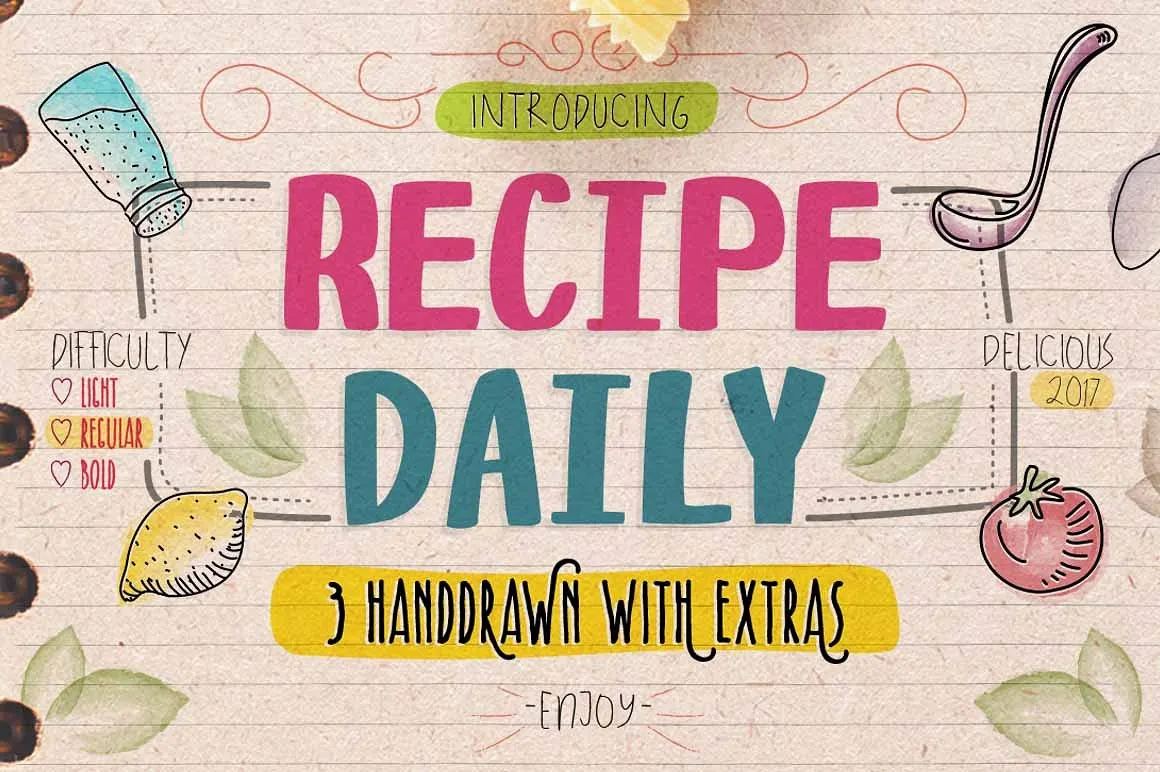
Recipe Daily Typeface – Download Grátis
Introduzimos Recipe Daily Typeface! Desenvolvida por StoricType, esta é uma fonte premium que você pode encontrar para compra na Críativa Mercado. Agora, recebemos a oportunidade de oferecer esta fonte gratuitamente para download. Recipe Daily Typeface surgiu inspirada em muitas letras encontradas nas anotações das refeições e foi projetada especificamente para as anotações de receitas e para o previsualização do Instagram. A fonte incorpora conceitos modernos em letras, logotipos, posters, camisetas e muito mais. Se você procura uma fonte que combine elegância com um toque contemporâneo, Recipe Daily é perfeitamente adequada. Sujeitada a um amplo espectro de aplicações, esta fonte é ideal para quem busca uma paleta de opções criativas em seu design. Seja para transformar suas anotações de receita em objetos únicos ou criar uma identidade visual atemporal para suas redes sociais e mercados, Recipe Daily está aqui para recompensá-lo com um estilo moderno e personalizado. Descubra agora a nova fonte que adicionará cor ao seu design. Descarregue e comece a explorar as infinitas possibilidades de criação oferecidas por esta font exclusiva!